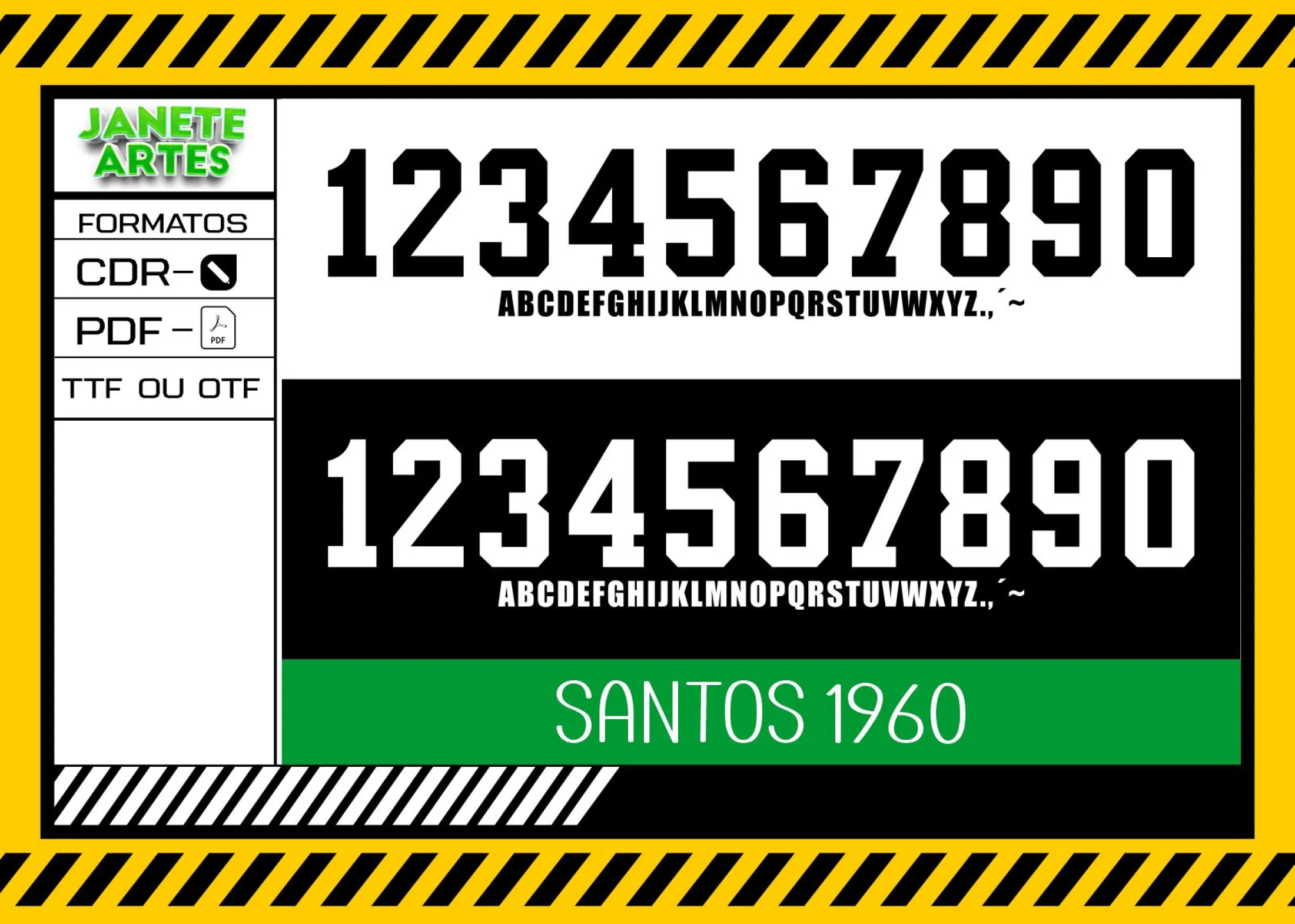
Fonte de Time Tipografia Santos 1960
Descubra o arquivo Fonte de Time Tipografia Santos 1960 para criar suas próprias camisetas com estilo vintage. Perfeito para personalizar camisas com logo no peito e estampa grande nas costas.
Uma história que marca gerações ⚽
Imagine uma noite de domingo, estádio cheio, torcida vibrando. Às vezes, o que une as pessoas é a paixão por detalhes autênticos, como a Fonte de Time Tipografia Santos 1960, que traz um resgate da história e cultura esportiva do Brasil. Essa fonte captura toda a emoção daqueles tempos clássicos, onde cada letra tinha personalidade e orgulho.
João, um fã do Santos FC, buscava uma forma de mostrar sua paixão criando camisetas personalizadas para o grupo de amigos. Ao encontrar o arquivo Fonte de Time Tipografia Santos 1960, ele pôde transformar aquela nostalgia em um visual moderno, com logo no peito e uma estampa grande nas costas cheia de charme e autenticidade.
• Fonte original do Santos 1960 pronta para ser aplicada em camisetas, camisas ou blusas.
Com o Fonte de Time Tipografia Santos 1960 você transfere a paixão do futebol para a moda, criando peças únicas e cheias de história. Aproveite para dar aquele toque especial na sua coleção ou no presente de quem ama futebol e design vintage!